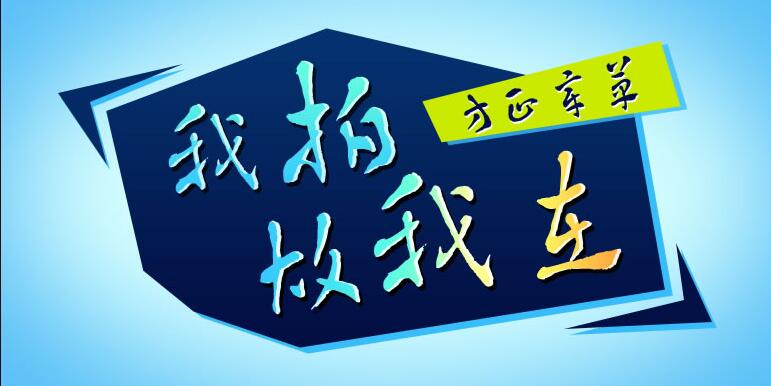
方正章草简体由方正字库方卫高潮设计师出品的一款艺术字体,行笔劲健,古雅沉雄,缓涩凝重,浑穆丰茂,敦厚朴实,不激不厉;构架骨气通达,适合应用于艺术设计、平面宣传设计、网页设计,书法等领域。
字体介绍
由中国书法家协会会员、国家级一级美术师卫高潮创作。卫高潮,1958年生于陕西,1980年从师吴三大,1985年加入中国书法家协会,2009年被评为国家一级美术师,现为陕西省书协副主席,已出版《卫高潮真草墨迹》、《卫高潮章草书作》等书法著作。章草,是书法的传统书体之一。是早期的草书,始于汉代,由草写的隶书演变而成。章草是“今草”的前身,与“今草”的区别主要是保留隶书笔法的形迹,上下字独立而不连写。方正章草体行笔劲健,古雅沉雄,缓涩凝重,浑穆丰茂,敦厚朴实,不激不厉;构架骨气通达,宽博疏朗,行次阔绰而气韵贯通,让人感觉灵动而富有韵律。